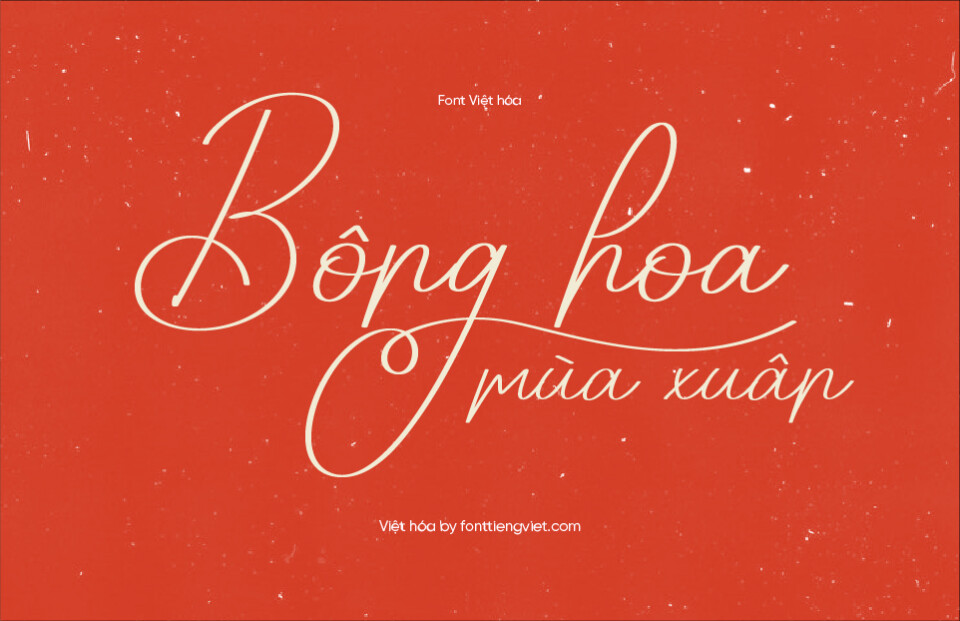
Giới thiệu bộ Font Việt hóa 1FTV VIP Daughter – tết
Chào đón không khí rộn ràng của mùa xuân, việc tìm kiếm một bộ Font Chữ ấn tượng là ưu tiên hàng đầu của các nhà thiết kế. Font Việt hóa 1FTV VIP Daughter – tết là sự kết hợp hoàn hảo giữa nét vẽ tay mềm mại và sự hiện đại tinh tế. Đây là công cụ đắc lực giúp bạn tạo ra những sản phẩm truyền thông mang đậm bản sắc văn hóa Việt Nam. Với các đường nét uốn lượn uyển chuyển, bộ font này gợi lên sự ấm áp, đoàn viên và may mắn trong những ngày đầu năm mới.
Ưu điểm nổi bật của Font Việt hóa 1FTV VIP Daughter – tết
Thiết kế tối ưu cho Tiếng Việt
Điểm mạnh nhất của Font Việt hóa 1FTV VIP Daughter – tết chính là việc xử lý các dấu thanh cực kỳ chuẩn xác. Bạn sẽ không còn lo lắng về lỗi nhảy chữ hay sai dấu khi gõ tiếng Việt. Sự chỉn chu trong từng ký tự giúp văn bản trở nên chuyên nghiệp và dễ đọc hơn đối với người xem.
Ứng dụng đa dạng trong học tập và công việc
Bộ font này rất phù hợp để làm thiệp chúc Tết, tiêu đề bài giảng điện tử hoặc trang trí báo tường tại trường học. Các em học sinh và thầy cô có thể dễ dàng sử dụng để tăng thêm tính thẩm mỹ cho các dự án sáng tạo của mình. Ngoài ra, nó còn được dùng rộng rãi trong thiết kế banner, poster sự kiện và bao bì sản phẩm quà tặng dịp xuân.